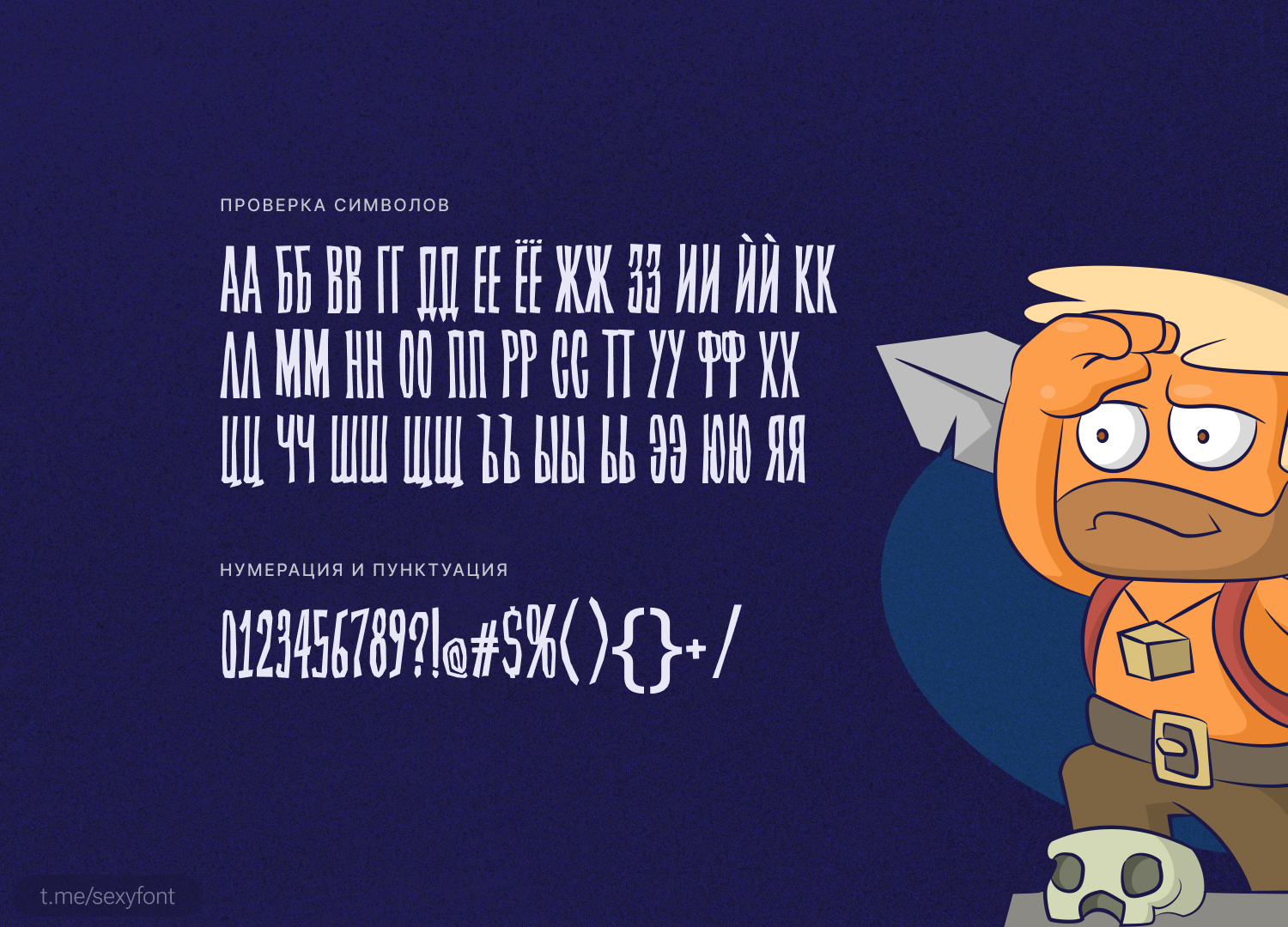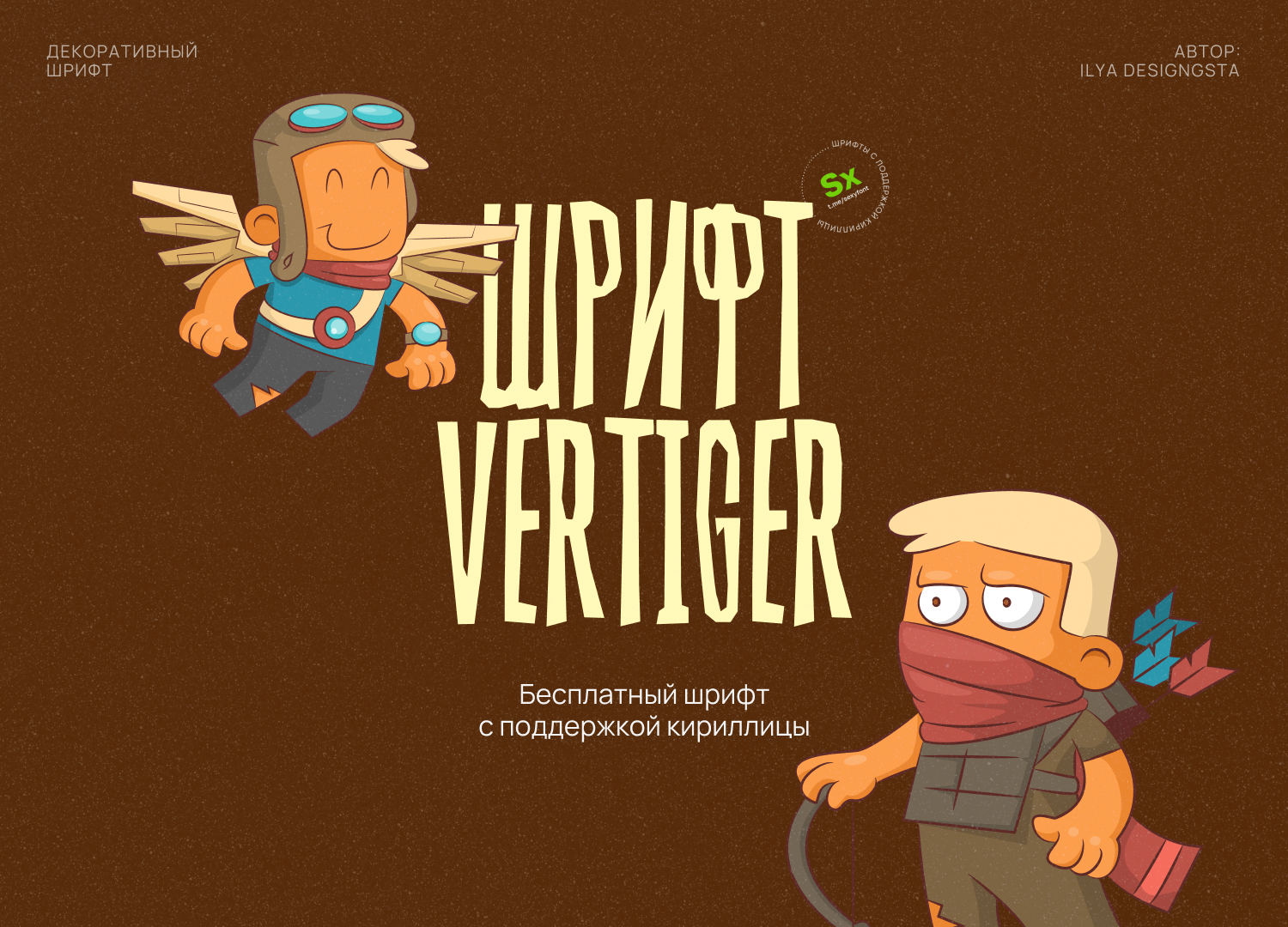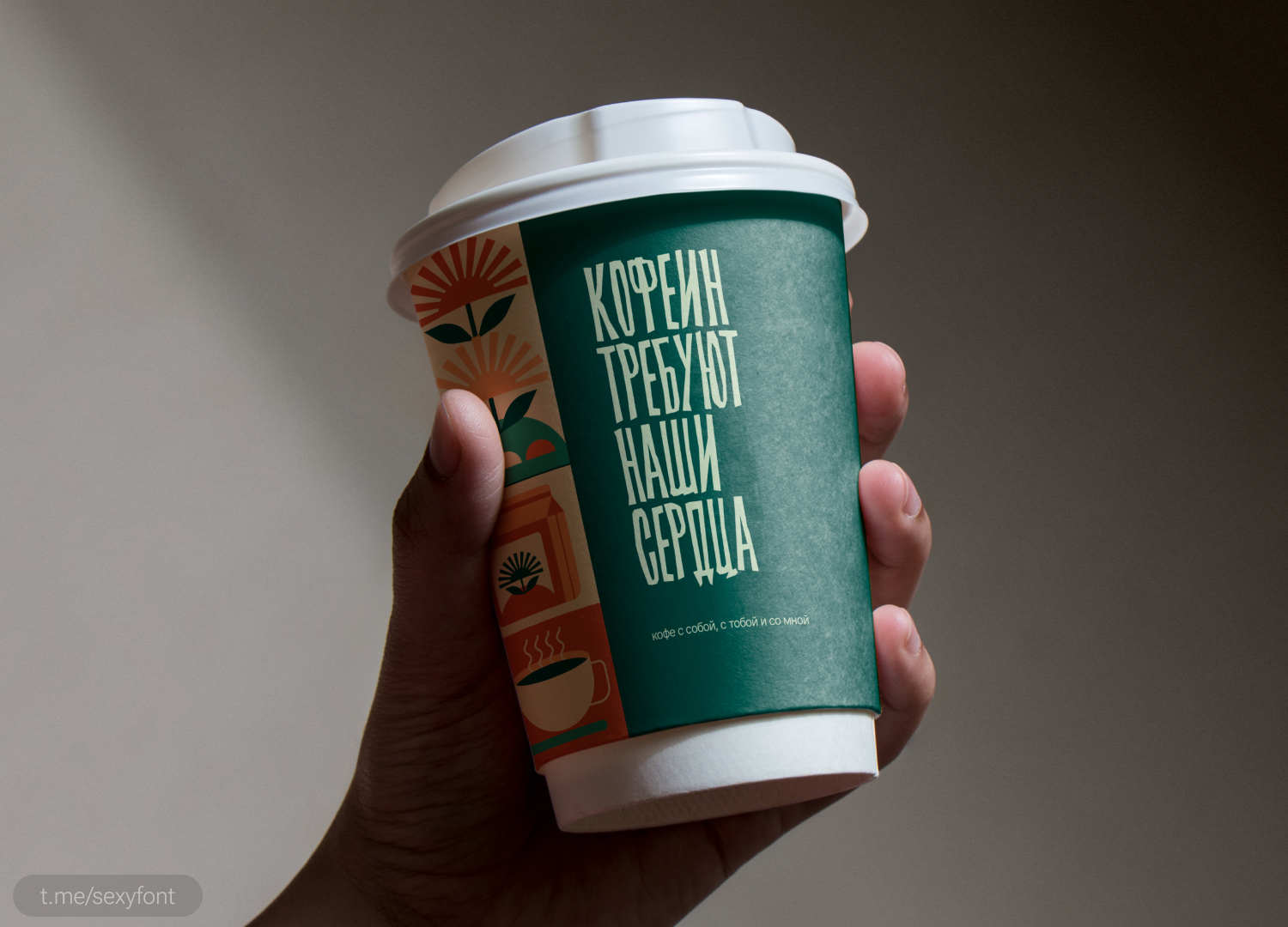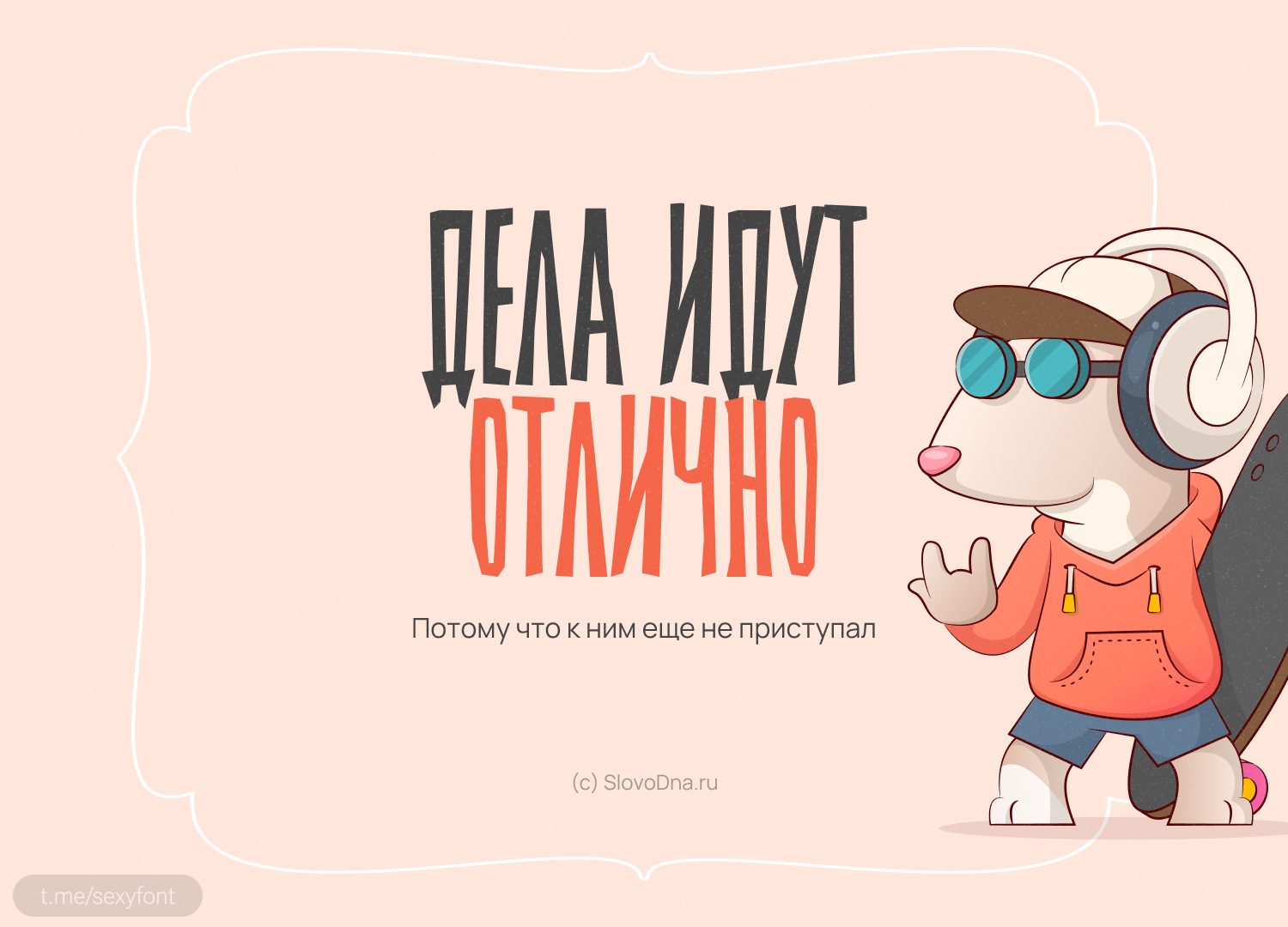
Vertiger. Это сжатый, грубый и ритмично повторяющийся шрифт, который передаёт загадочное очарование мистических кинопостеров 1950-х и 1960-х годов.Автор: Ilya Designgsta